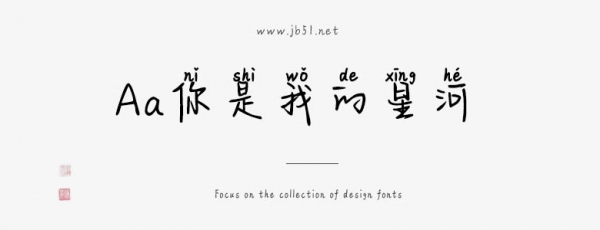
Aa你是我的星河是一款不錯(cuò)的藝術(shù)字體,由Aa字庫(kù)出品,字體筆觸適中,書(shū)寫(xiě)流暢,擁有字符數(shù)9983和字形數(shù)16805,具有很好的視覺(jué)感,適合應(yīng)用于藝術(shù)設(shè)計(jì)、平面宣傳設(shè)計(jì)、網(wǎng)頁(yè)設(shè)計(jì),書(shū)法字帖等領(lǐng)域,需要的朋友可以前來(lái)本站下載。